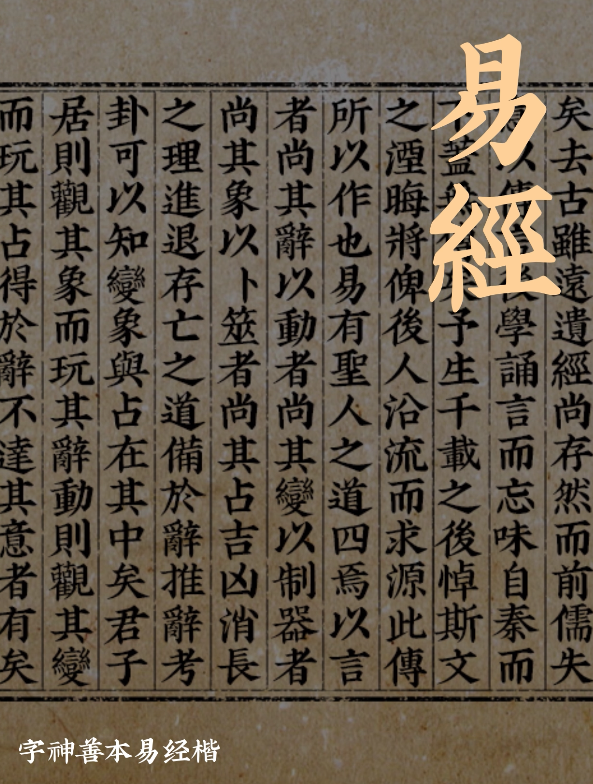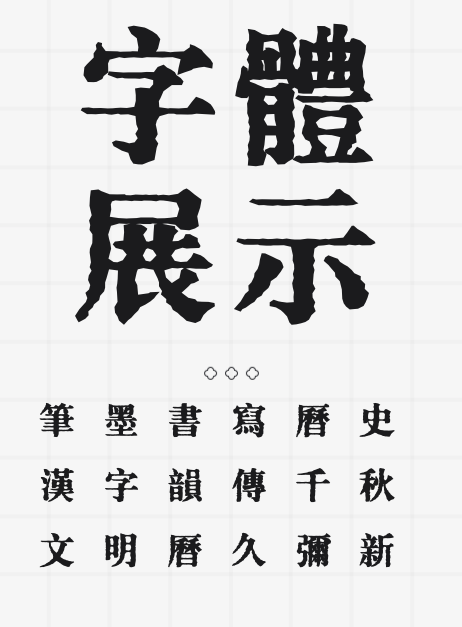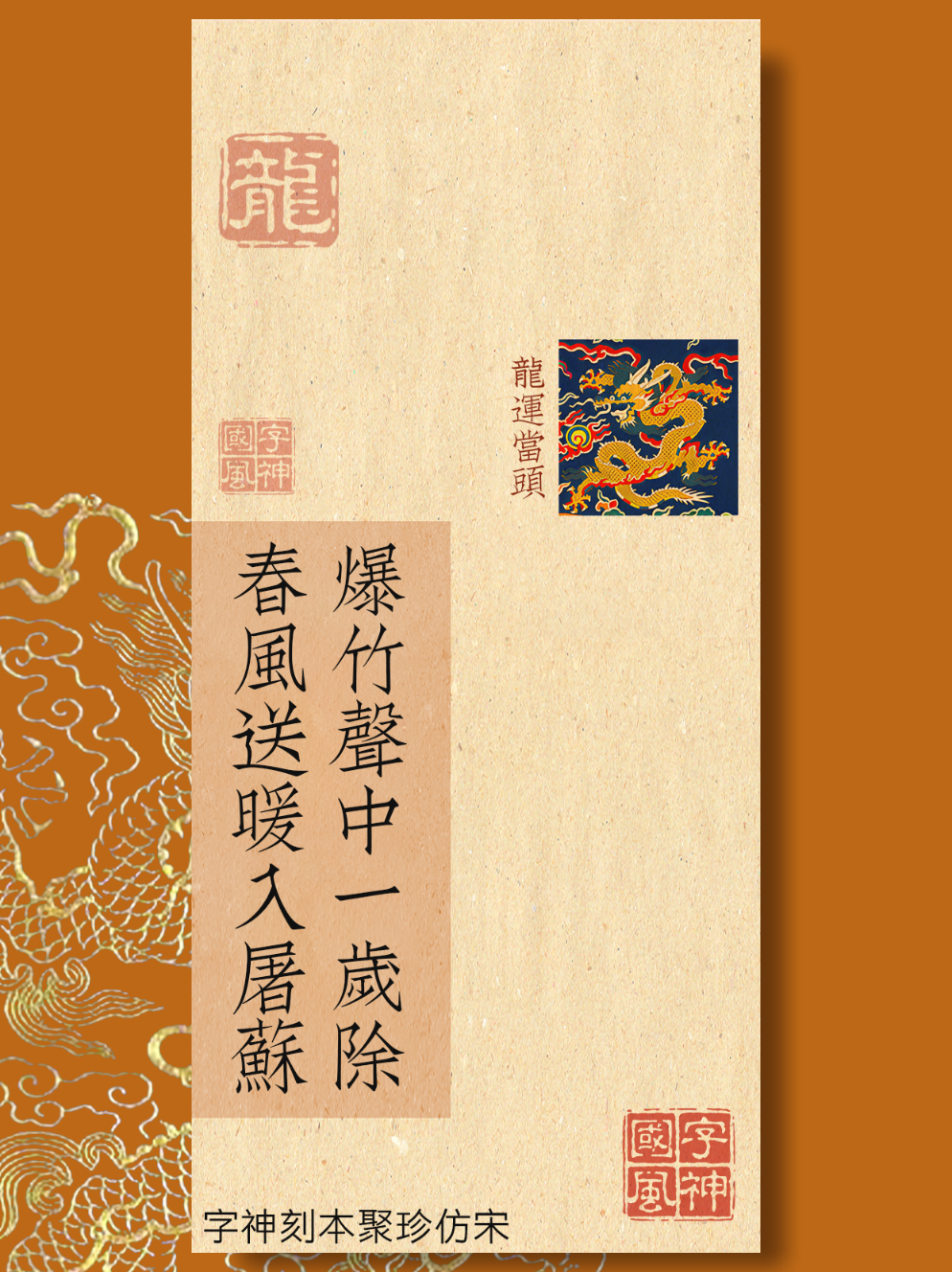
🎨古风韵味爆棚!这3款字体让国风品牌秒变文化担当✨
Hey小伙伴们,今天咱们来聊聊那些能让国风品牌瞬间提升格调的神仙字体!👑 是不是每次看到那些充满文化底蕴的设计就心痒痒?别急,我这就给你种草三款,保证让你的品牌文案美得不像话!🌸
首推🌟【字神刻本聚珍仿宋】,这款字体简直就是古风界的清流!它借鉴了宋代刻本的韵味,每一笔一划都透露着历史的沉淀和文化的雅致。📜 用它来书写品牌故事或宣传语,瞬间让你的国风品牌仿佛穿越千年,与古人对话,那份古典美,简直绝了!👏
再来看看🌈【字神善本易经楷】,这款楷体融入了《易经》的智慧与哲学,字形既有楷书的工整,又不失灵动变化,就像是书法大师笔下的即兴之作。🖌️ 对于想要传达智慧、平衡理念的国风品牌,这款字体无疑是最佳选择,让人一眼难忘,回味无穷!🤔
最后压轴的是💥【汉字之美墨染大标宋】,听名字就能感受到那股浓厚的文化气息了吧?这款大标宋字体,每一笔都像是在宣纸上轻轻晕染开来的墨滴,既有力量又不失柔美。🌊 用来做大标题或是重点强调,绝对能让你的国风设计作品在众多设计中脱颖而出,成为焦点!🔥